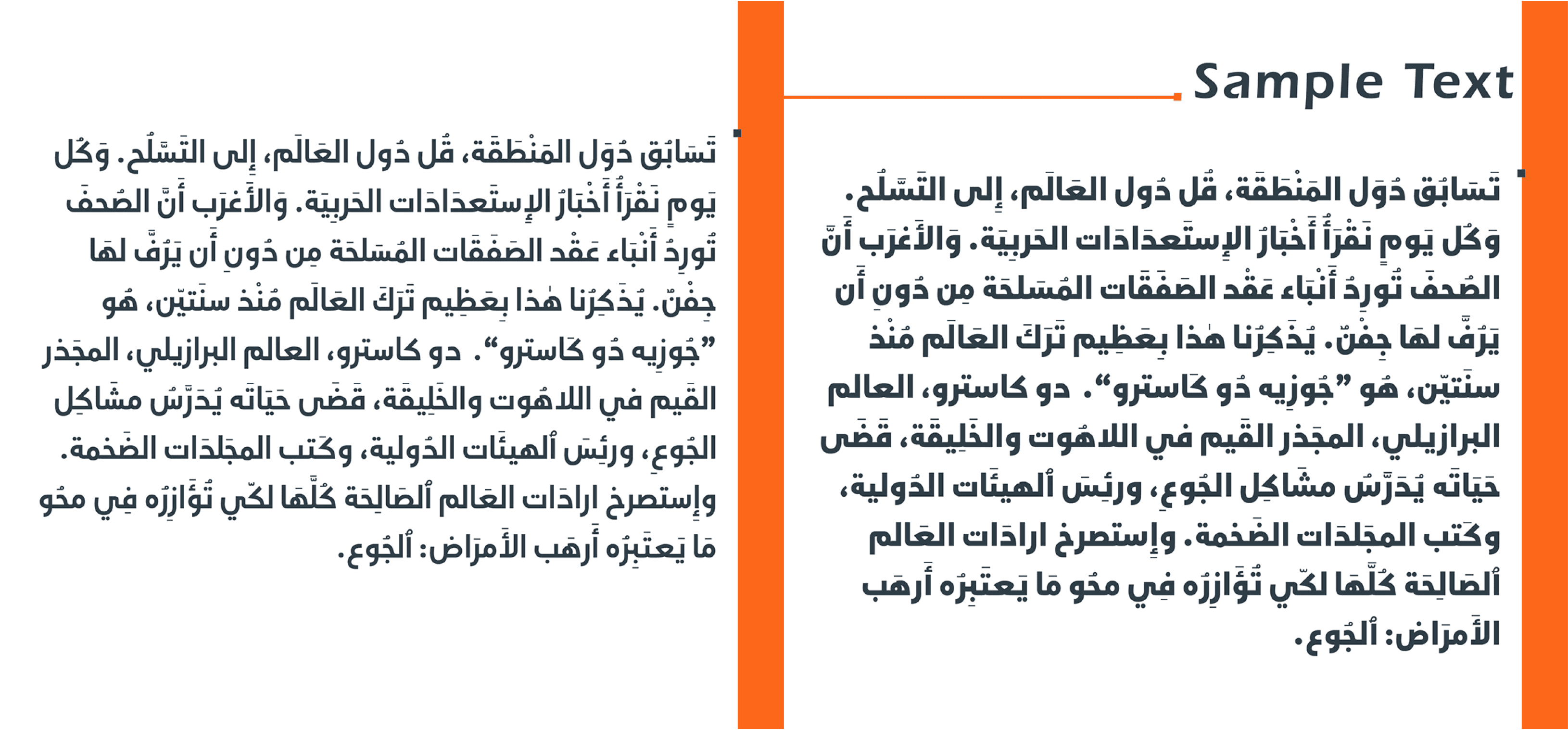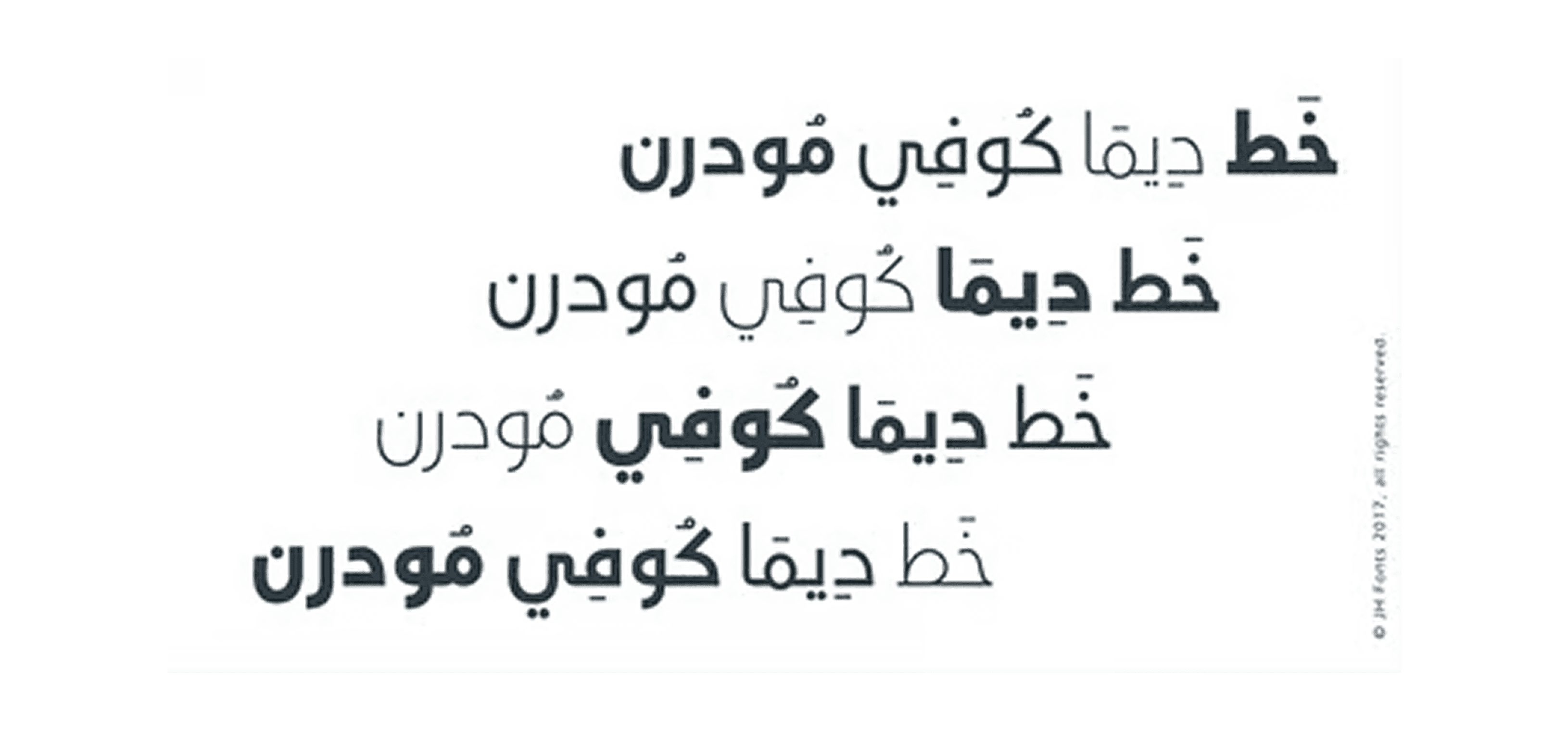
هو خط بأسلوب عصري، تم تصميمه بالاعتماد على أسلوب الكوفي وتصنيف الخطوط اللاتينية الهندسية، ويُعد مثاليًا للهويات البصرية، العلامات التجارية، ولوحات الإرشاد.